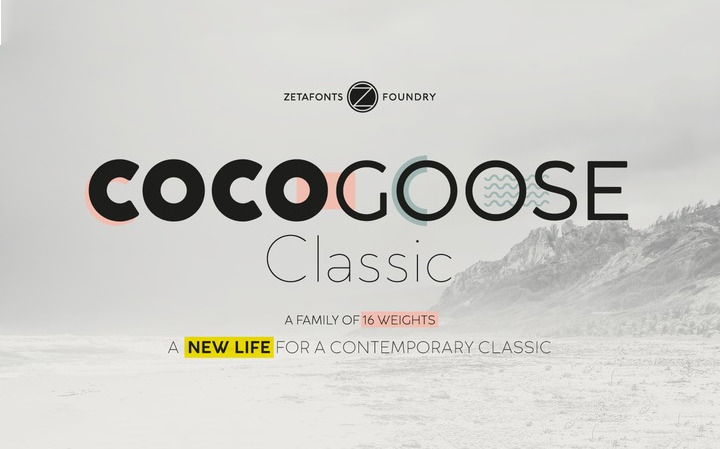
Cocogoose Classic Font Famly – Download Grátis
Aproveite esse novo design visual com a Cocogoose Classic Font Family, uma criação do Zetafonts concebida pelo designer Cosimo Lorenzo Pancini em 2012 para um tipo de exibição geometricamente equilibrado. Com suas linhas retas pouco pronunciadas e um x-ponto extremo, essa fonte é ideal não apenas para destaque, mas também para os logotipos. Suas versões ultrabold permitem que ela ganhe destaque notável em qualquer layout gráfico, especialmente quando combinada com as versões decorativas da linha Cocogoose. A popularidade de Cocogoose como fonte de exibição é tão grande que muitos designers o usam tanto para criar logotipos memoráveis quanto para destacar informações importantes em sua apresentação visual.